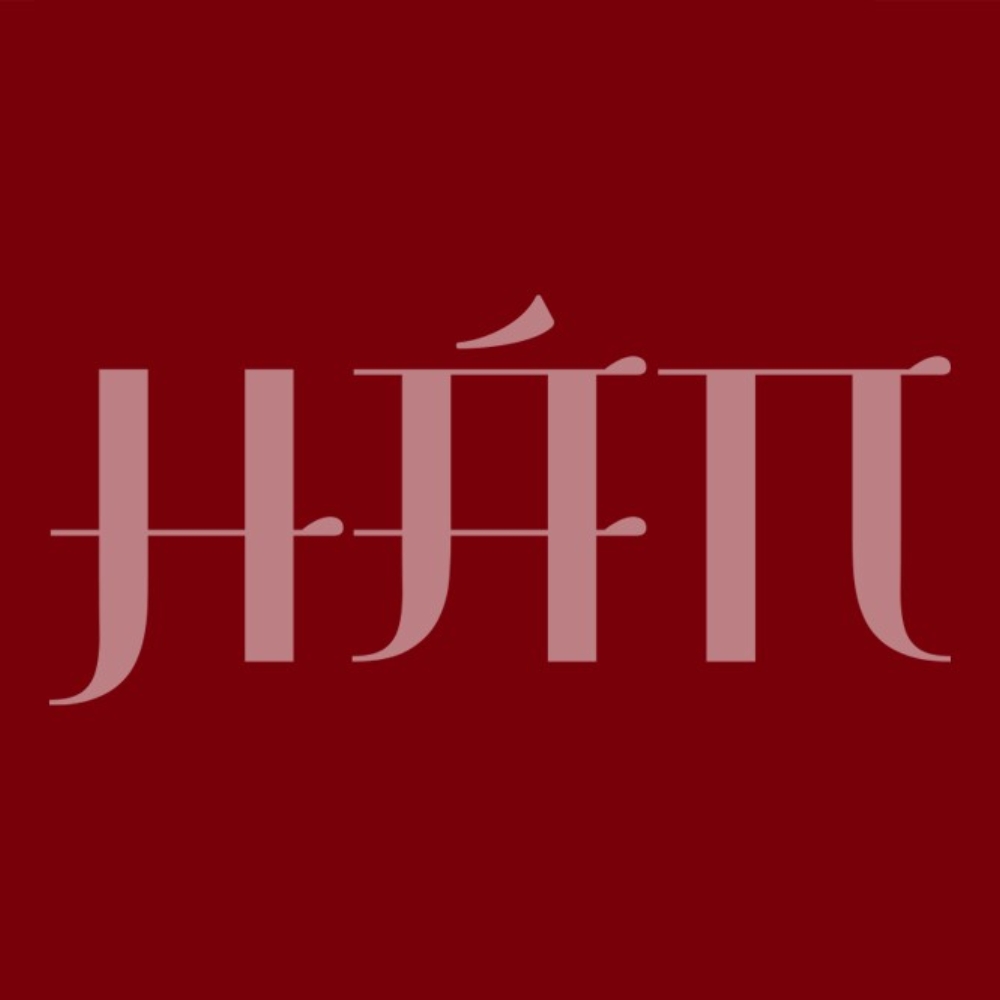
Font chữ Hán Việt hóa là font chữ truyền thống mang nét văn hóa cổ điển Việt Nam, được sử dụng trong thiết kế sản phẩm văn hóa, quà tặng truyền thống và in ấn cho bảo tàng, di tích lịch sử. Font chữ Nôm việt hóa đặc biệt quan trọng trong bảo tồn di sản văn hóa và thiết kế sản phẩm mang đậm bản sắc dân tộc.
Ở bài viết này, In Viva giới thiệu bộ sưu tập font chữ hán Việt hóa với đầy đủ font chữ Hán, chữ Nôm phù hợp cho thiết kế quà tặng văn hóa, sản phẩm lưu niệm di tích và in ấn tài liệu lịch sử.
Tham khảo 15+ mẫu font chữ Hán Việt hóa đẹp
Font chữ Hán và chữ Nôm mang phong cách truyền thống, cổ điển, thường được sử dụng trong các dự án văn hóa, lịch sử. Dưới đây là 15+ mẫu font chữ hán và chữ Nôm đã được số hóa để sử dụng trong thiết kế hiện đại:
Nhóm font chữ Hán Nôm chuẩn:
- HAN NOM A – Font chữ Hán Nôm chuẩn, phổ biến nhất cho nghiên cứu.
- HAN NOM B – Phiên bản bổ sung với nhiều ký tự đặc biệt hơn.
- Nom Na Tong – Font chữ Nôm với nét thư pháp truyền thống.
- Viet Han Nom – Kết hợp chữ Hán và chữ Nôm trong một font.
- Han Nom Revival – Font chữ Hán Nôm được phục dựng từ văn bia cổ.
Nhóm font chữ Hán phong cách thư pháp:
- Chinese Calligraphy VN – Nét thư pháp Trung Quốc việt hóa.
- Kai Ti VN – Font chữ Hán phong cách Khải Thư.
- Song Ti VN – Phong cách Tống Thể cổ điển.
- Ming Imperial – Chữ Hán phong cách triều đại Minh.
Nhóm font chữ Nôm đặc biệt:
- Nom Preservation – Font bảo tồn chữ Nôm cho tài liệu cổ.
- Ancient Vietnam Script – Chữ Nôm phong cách văn bia đá.
- Chu Nom Traditional – Chữ Nôm truyền thống, chuẩn chỉnh.
- Nom Stone Inscription – Nét khắc bia, chạm khắc.
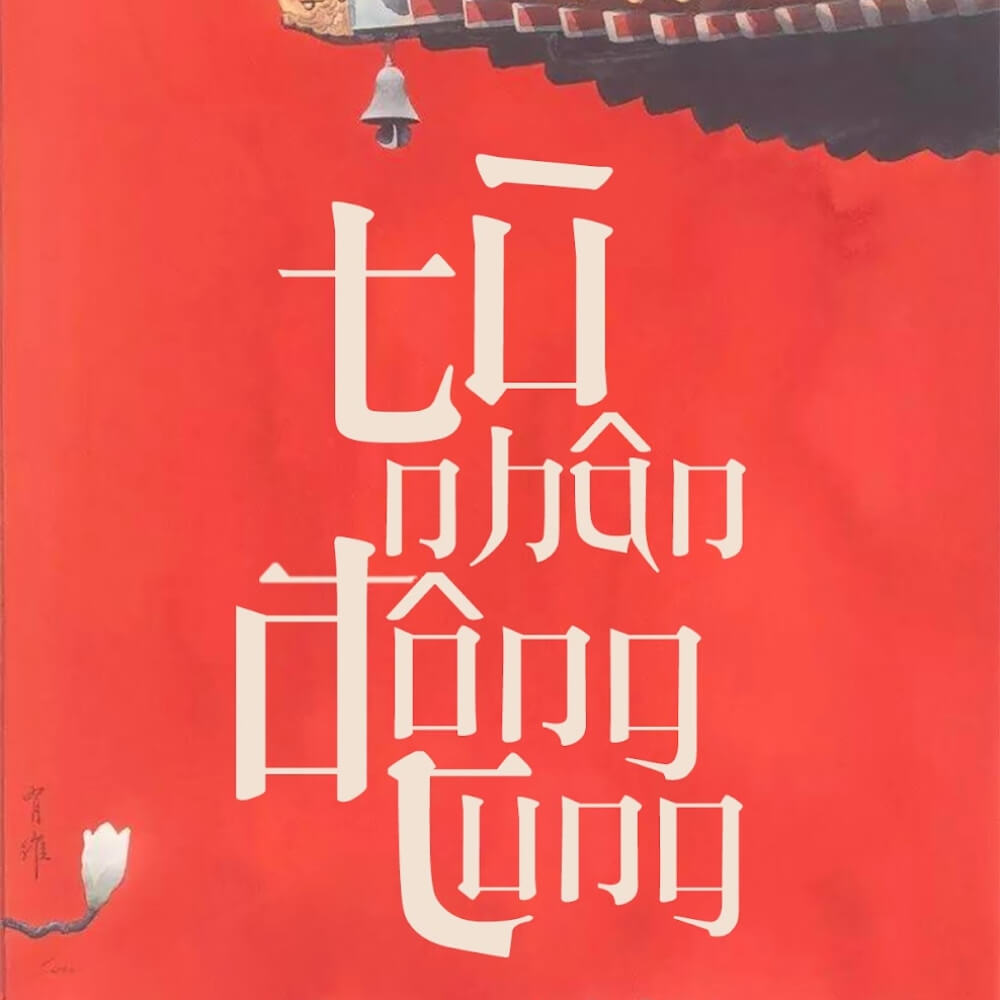
Font chữ Hán Việt hóa là lựa chọn phù hợp cho những thiết kế mang phong cách cổ điển, truyền thống và đậm nét văn hóa Á Đông. Các font này được tối ưu hiển thị tiếng Việt, giúp đảm bảo dấu câu rõ ràng, đồng thời giữ nguyên vẻ đẹp thư pháp đặc trưng của chữ Hán và chữ Nôm. Dưới đây là bảng tổng hợp các font chữ Hán và chữ Nôm phổ biến, được nhiều người sử dụng trong thiết kế hiện nay:
Tên font |
Phong cách |
Ứng dụng in ấn tốt nhất |
HAN NOM A |
Chữ Hán Nôm chuẩn, nghiên cứu. | Sách lịch sử, tài liệu nghiên cứu văn hóa. |
Nom Na Tong |
Chữ Nôm nét thư pháp truyền thống. | Bảng hiệu đình chùa, di tích lịch sử. |
Viet Han Nom |
Kết hợp Hán + Nôm. | Tài liệu song ngữ, giáo trình lịch sử. |
Chinese Calligraphy VN |
Thư pháp Trung Quốc việt hóa. | Tranh thư pháp, quà tặng văn hóa cao cấp. |
Nom Stone Inscription |
Nét khắc bia đá, văn bia. | Biển chỉ dẫn di tích, bia tưởng niệm. |
Ancient Vietnam Script |
Chữ Nôm cổ, văn bia. | Bảo tàng, khu di tích văn hóa. |
Ứng dụng font chữ Hán trong thiết kế quà tặng văn hóa
Font chữ Hán và chữ Nôm mang giá trị văn hóa đặc biệt trong thiết kế sản phẩm truyền thống:
- Bảo tồn di sản văn hóa: Font chữ Hán Nôm giúp số hóa và lưu giữ các văn bản cổ, bia đá, sắc phong triều đại, góp phần bảo tồn di sản văn hóa phi vật thể của dân tộc.
- Tạo cảm giác trang trọng, uy nghi: Chữ Hán Nôm với nét thư pháp cổ điển tạo cảm giác trang trọng, phù hợp cho sản phẩm văn hóa, lịch sử, đình chùa, di tích.
- Kết nối với truyền thống: Sản phẩm sử dụng chữ Hán Nôm giúp người xem kết nối với truyền thống, lịch sử ngàn năm văn hiến của dân tộc.
- Phù hợp thị trường du lịch văn hóa: Quà lưu niệm, sản phẩm văn hóa sử dụng chữ Hán Nôm rất được du khách nước ngoài ưa chuộng vì tính độc đáo, bản sắc.
Font chữ Hán việt hóa xuất hiện trong nhiều sản phẩm văn hóa:
- Túi vải, túi giấy kraft cho bảo tàng, khu di tích văn hóa.
- Hộp quà tặng văn hóa: trà, gốm sứ, thủ công mỹ nghệ truyền thống.
- Thiệp chúc Tết truyền thống, thiệp mừng thọ, liễn xuân.